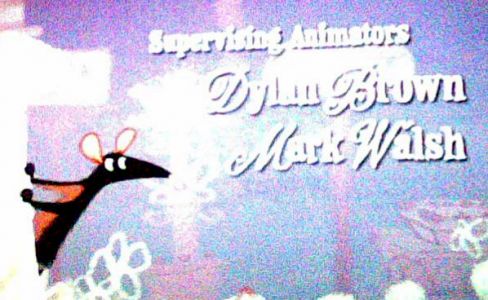
Abspann in Ratatouille
wer hat Ratatouille gesehen und sich über den Abspann gefreut, oder meinetwegen auch geärgert . . . ?
Weiß jemand welche Schrift die da benutzt haben? Oder ist es gar eine Sonderanfertigung? Könnte auch eine Mischung sein, denn die Versal-Swashes scheinen nicht ganz zu den Minuskeln zu passen, was ja auch wieder einen gewissen Charme erzeugt. Die Schrift kommt auch im DVD-Menu vor.
mir ist die schrift in dem vorspann von Ratatouille auch aufgefallen, es dürfte sich allerdings
nicht um die schrift handeln welche alexander gezeigt hat. die aus dem vorspann ist irgendwie
verspielter. ein schlechtes bild gibts hier:
ich versuche mal bessere bilder aufzutreiben. mir hat sie ebenfalls gut gefallen.